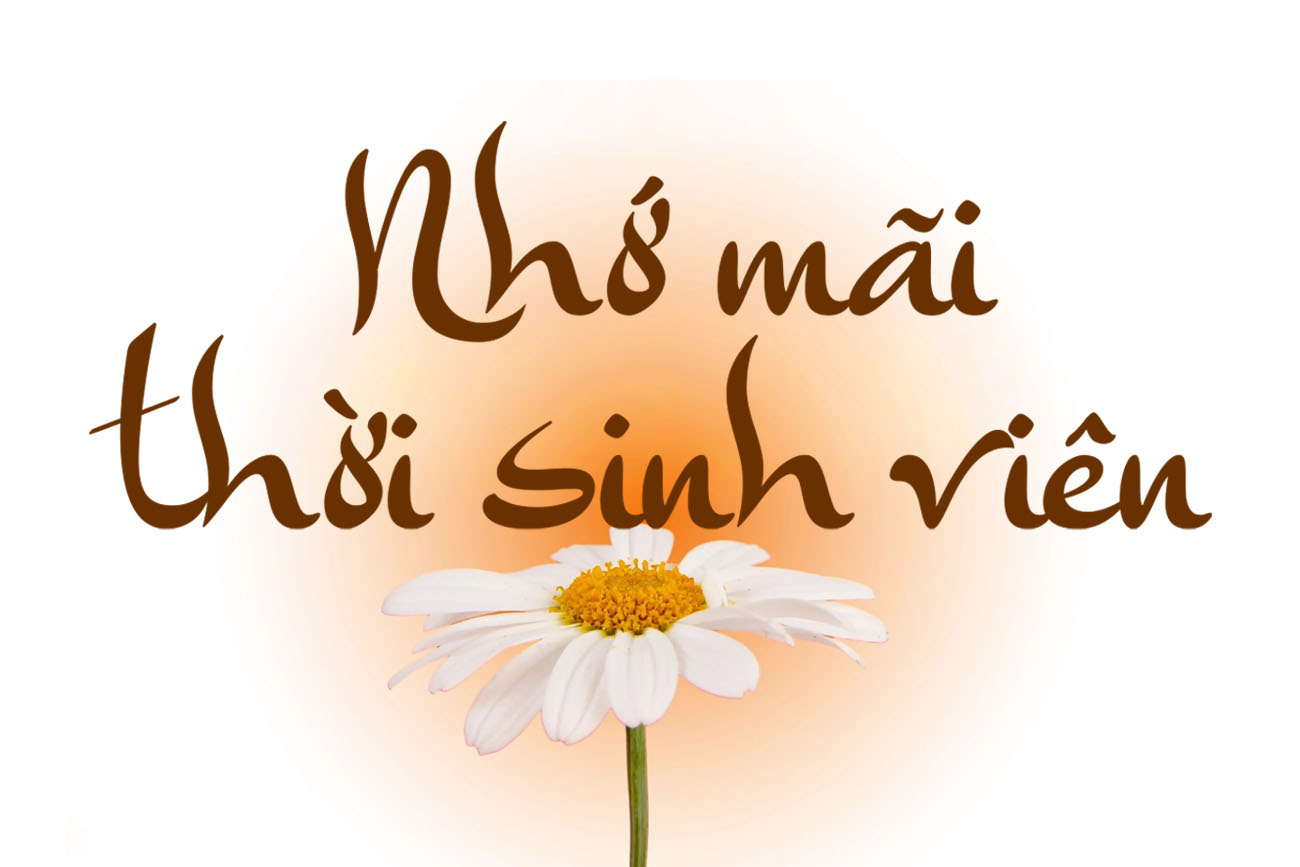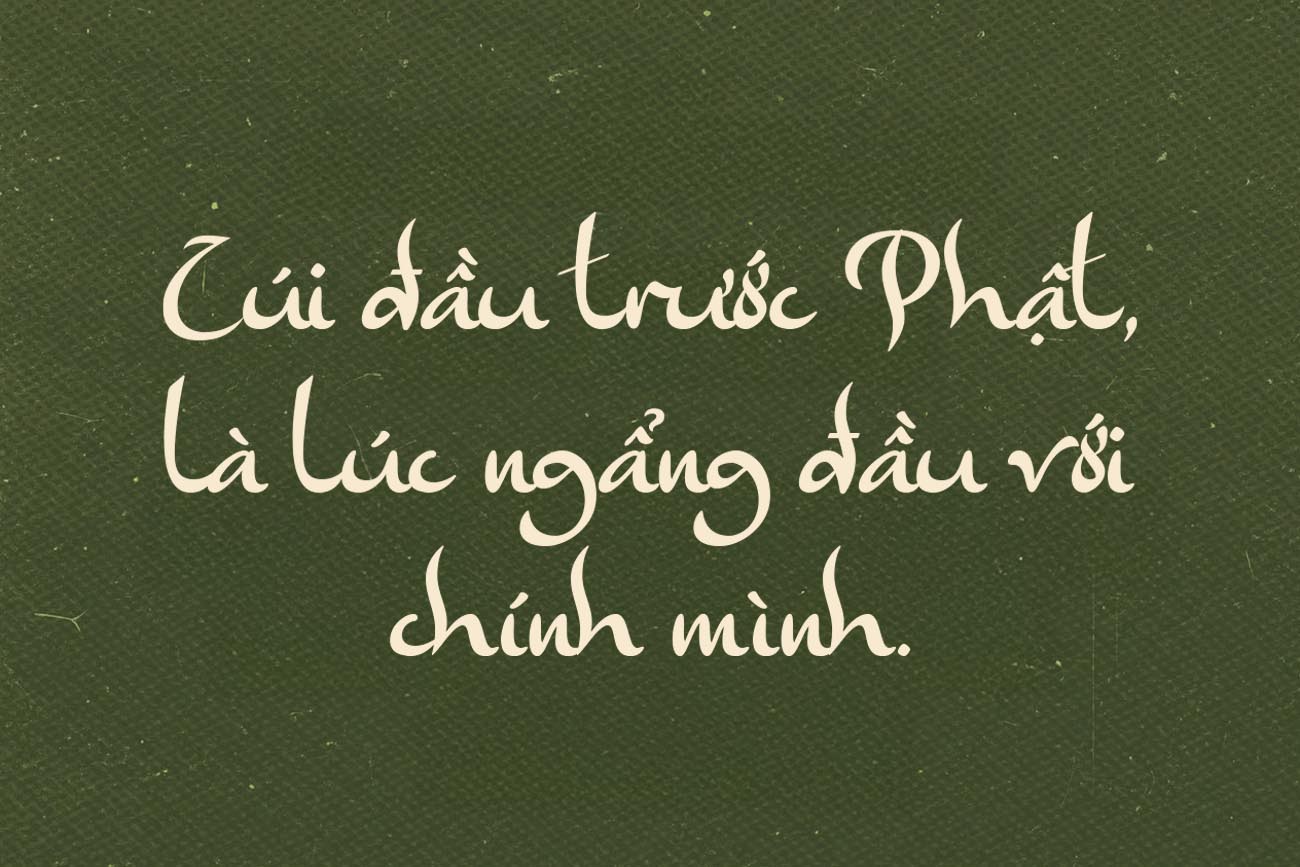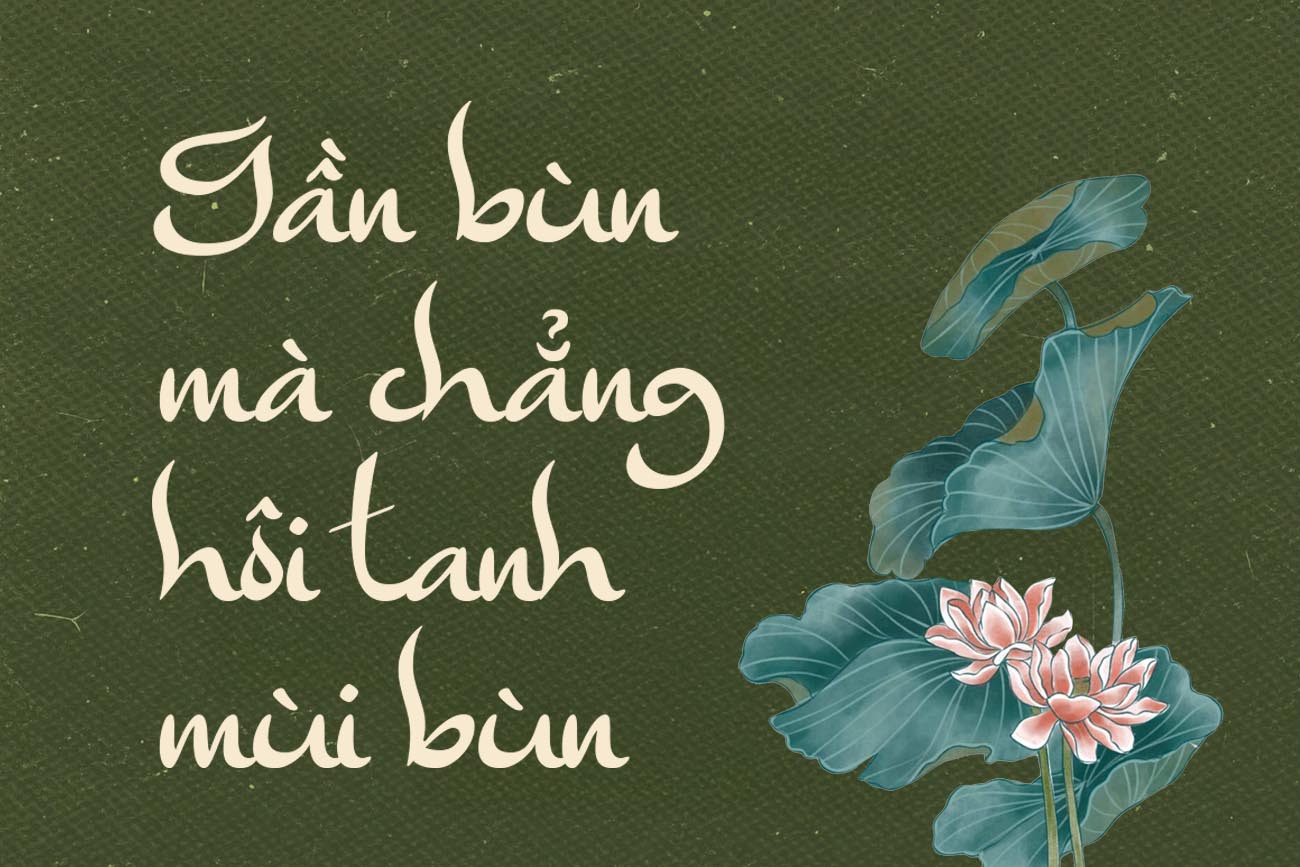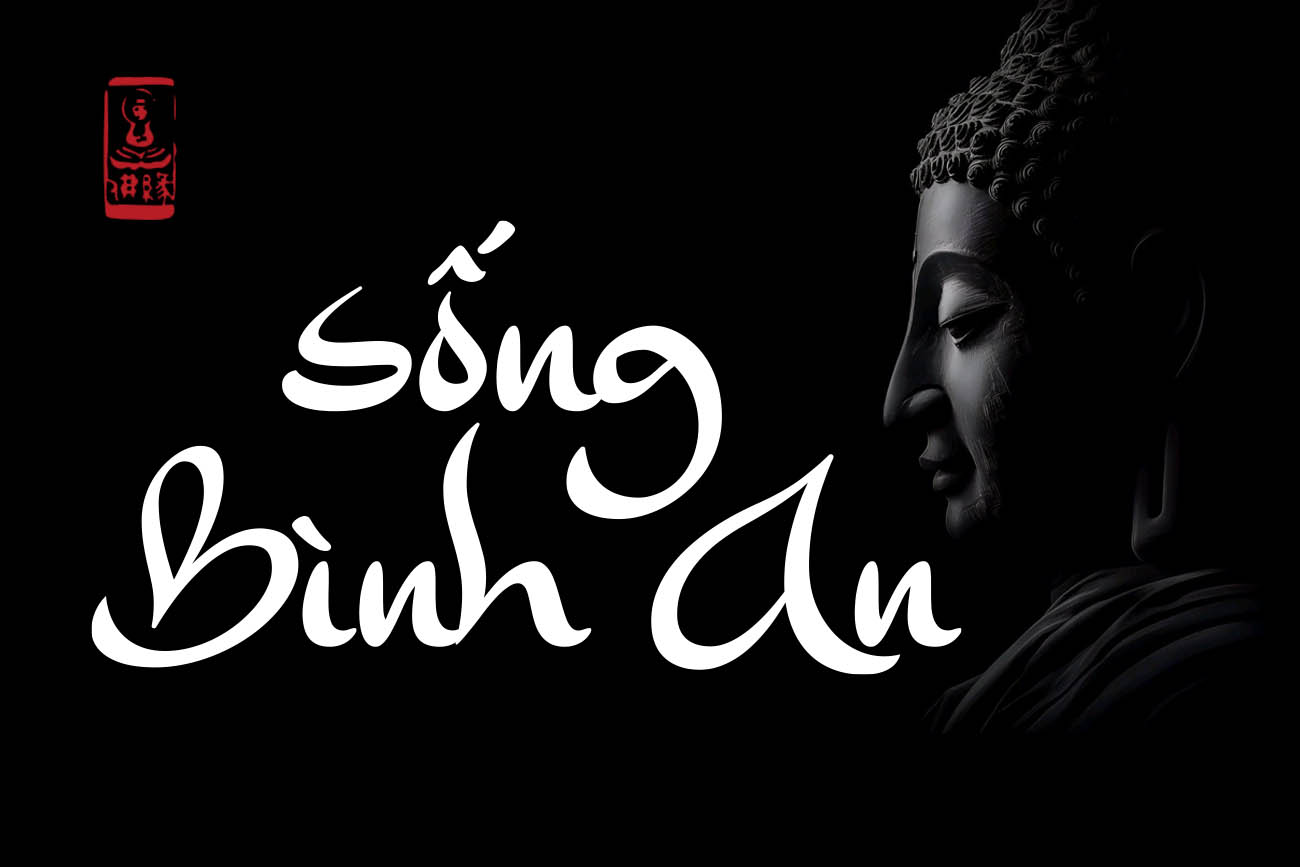
Siêu phẩm font chữ phong cách Ả Rập TH Elmirad Việt Hóa
Trong thế giới thiết kế đồ họa, việc tìm kiếm một bộ phông chữ mang đậm bản sắc văn hóa nhưng vẫn đảm bảo tính ứng dụng cao là một thử thách thú vị. Hôm nay, chúng tôi xin giới thiệu đến cộng đồng Designer bộ font TH Elmirad, một phiên bản Việt hóa hoàn hảo từ tác phẩm gốc Elmirad của tác giả Kong Font nổi tiếng.
Vẻ đẹp độc đáo từ Trung Đông
Nguyên bản Elmirad được Kong Font thiết kế dựa trên cảm hứng từ nghệ thuật thư pháp Trung Đông. Đây là một dạng font ả rập (Arabic simulation font) với các nét chữ Latin được cách điệu khéo léo để mô phỏng hình thái của chữ Ả Rập. Những đường cong mềm mại, các nét móc đặc trưng và độ tương phản dày mỏng tinh tế tạo nên một tổng thể vừa lạ mắt, vừa cuốn hút.
Sự độc đáo này giúp TH Elmirad trở thành lựa chọn lý tưởng cho các ấn phẩm cần sự huyền bí, trang trọng hoặc mang tính lịch sử. Không chỉ dừng lại ở phong cách Trung Đông, với cách thể hiện nét cọ phóng khoáng, bộ font này còn rất phù hợp khi được sử dụng như một font cổ trang cho các poster phim, bao bì sản phẩm truyền thống hoặc giao diện game kiếm hiệp.
Font TH Elmirad Việt Hóa: Tuyệt Phẩm Typography Phong Cách Ả Rập Huyền Bí
Ứng dụng đa dạng trong thiết kế tâm linh và văn hóa
Điểm đặc biệt của TH Elmirad nằm ở khả năng biến hóa linh hoạt. Bên cạnh vẻ đẹp ngoại lai, các đường nét của font chữ này còn gợi nhớ đến sự tĩnh tại, trang nghiêm. Chính vì vậy, nhiều Designer đã sáng tạo sử dụng nó như một font nhà chùa trong các thiết kế liên quan đến Phật giáo, ấn phẩm tâm linh, hoặc các trích dẫn thiền đạo. Sự uyển chuyển của con chữ giúp truyền tải thông điệp một cách nhẹ nhàng nhưng đầy sức nặng.
Bản Việt hóa chỉn chu từ team TH
Để mang vẻ đẹp của Elmirad đến gần hơn với người dùng Việt, team TH đã thực hiện công đoạn Việt hóa vô cùng tỉ mỉ. Bộ font TH Elmirad không chỉ được bổ sung đầy đủ các dấu tiếng Việt theo chuẩn Unicode mà còn được tinh chỉnh lại kerning (khoảng cách giữa các ký tự) và các dấu phụ để đảm bảo sự cân đối khi gõ văn bản.
Việc sở hữu phiên bản Việt hóa này giúp các Designer xóa bỏ hoàn toàn nỗi lo lỗi font khi xử lý các nội dung tiếng Việt, đồng thời giữ nguyên được tinh thần nghệ thuật mà tác giả Kong Font muốn truyền tải.